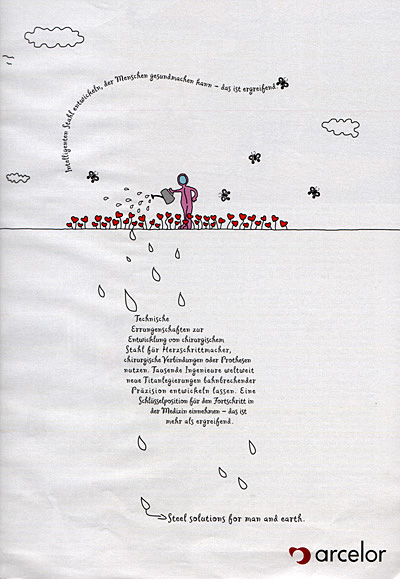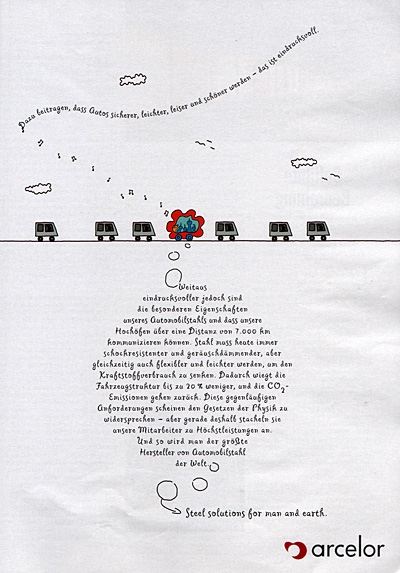
Es lockt die SchreibschriftDas global agierende Stahlkonsortium Arcelor wirbt diese Woche in führenden
deutschen Printmedien für »Steel solutions for man and earth«:
mit auffälligen, typografisch gestalteten Ganzseitenmotiven, in denen sich
eine Schreibschrift verführerisch übers Papier schlängelt.
Mehrere Kunden haben sich bereits bei FontShops Schrifterkennung nach
dieser außergewöhnlichen Script erkundigt. Hier kommt die Lösung
![]() Buchstaben fliegen, Zeilen tröpfeln: eine zarte Bildsprache für den harten Rohstoff Stahl. Die Hauptrolle spielt eine gelockte Schreibschrift namens »Cafe Mimi«.
Die Schrift der Arcelor-Kampagne: MVB Cafe Mimi, 1996 entworfen von Kanna Aoki, hier probesetzen ... Falls Sie eine ähnliche Schrift einsetzen möchten, dann empfehlen wir folgende lockige Script-Alternativen: ![]() ITC Clover, 1997 entworfen von Jill Bell, hier probesetzen ...
Elliott’s Venus Dioxide , 1993 entworfen von Elliot Peter Earls, hier probesetzen ...
Emmascript , 1996 entworfen von Kanna Aoki, hier probesetzen ...
ITC Fling, 1995 entworfen von Michael Gills, hier probesetzen ...
FF Fontesque Text, 1998 entworfen von Nick Shinn, hier probesetzen ...
Garden Weasel, 1995 entworfen von Betsy & Kelly Kopshina, hier probesetzen ...
Giddyup, 1994 entworfen von Laurie Szujewska, hier probesetzen ...